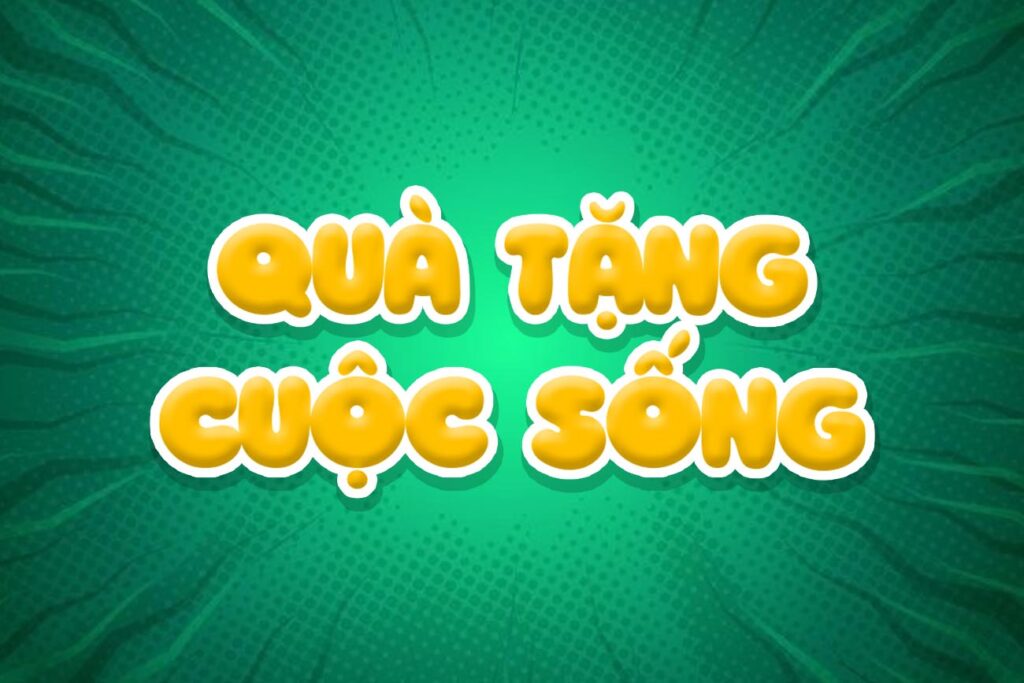
Font chữ tròn mập là nhóm phông chữ sở hữu các đường nét đầy đặn và góc bo mịn màng, mang lại cảm giác vui tươi, gần gũi và đầy năng lượng. Trong lĩnh vực kiến trúc và trang trí nội thất, việc sử dụng các kiểu chữ này giúp làm dịu đi sự thô cứng của các khối hình học, tạo nên sự cân bằng thị giác thú vị cho người xem.
Đặc điểm thẩm mỹ của dòng font chữ tròn mập trong thiết kế
Nét lôi cuốn đặc trưng của phông chữ tròn mập nằm ở cấu trúc chữ không có cạnh sắc, mô phỏng sự mềm mại của các khối hình học bo tròn. Thiết kế này tạo ra một diện mạo thân thiện, giúp thông điệp truyền tải trở nên dễ tiếp nhận và mang tính nhân bản cao hơn. Việc sử dụng font chữ bo tròn góc Việt hóa chuẩn Unicode giúp loại bỏ hoàn toàn tình trạng lỗi dấu thanh, đảm bảo các ký tự đặc biệt như “đ, ă, ơ” luôn cân đối với khung chữ chính, duy trì nhịp điệu thẩm mỹ ổn định cho văn bản.
Sự ổn định của bộ phông này còn thể hiện ở khả năng thu hút thị giác mạnh mẽ. Với trọng lượng nét dày, các kiểu chữ tròn mập chiếm lĩnh không gian hiển thị một cách có ý đồ, giúp các tiêu đề trở nên nổi bật mà không cần quá nhiều hiệu ứng đồ họa phức tạp. Đây là giải pháp phù hợp để định hình phong cách cho các không gian nghỉ dưỡng, nhà lắp ghép cho trẻ em hoặc những thương hiệu muốn khẳng định sự trẻ trung và tư duy đổi mới trong thiết kế.
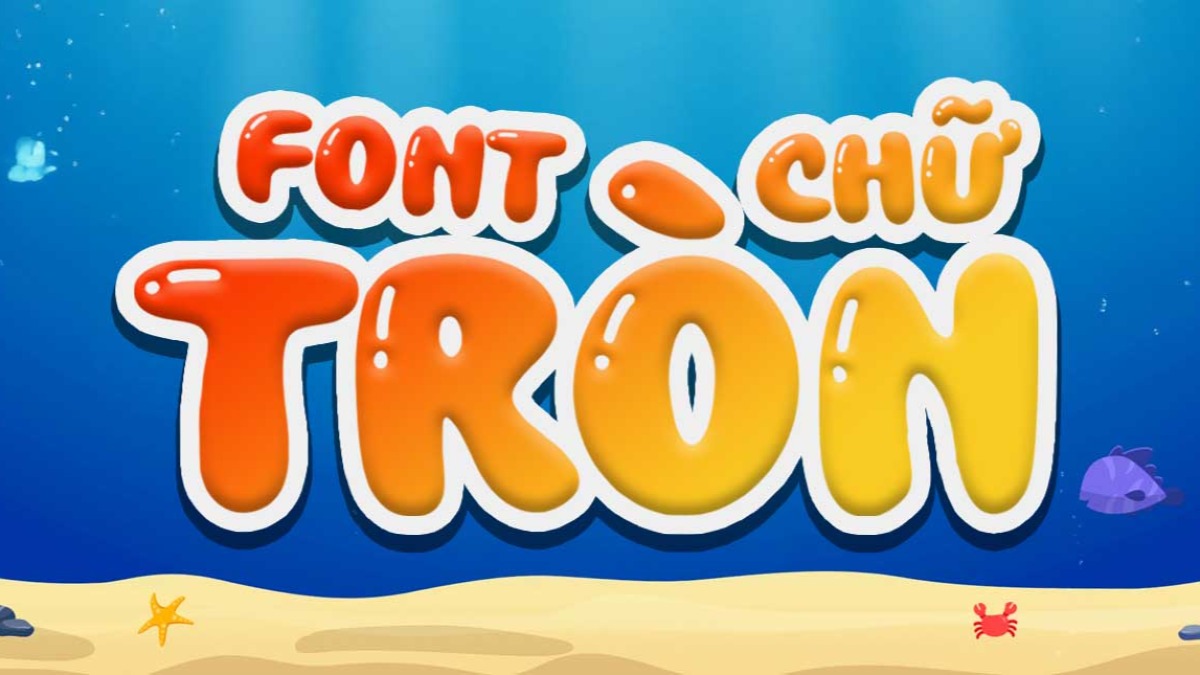
| Phân loại phong cách | Rounded Sans-serif / Display / Playful |
| Nhóm phông tiêu biểu | Baloo, Quicksand, VAG Rounded, Comfortaa |
| Mục đích phù hợp | Bảng hiệu homestay, logo, decor phòng trẻ em |
Tư vấn lựa chọn: Để bản thiết kế đạt được hiệu quả thị giác hài hòa, bạn nên phối hợp font bo tròn Việt hóa nét dày cho các tiêu đề chính và sử dụng phông tròn nét mảnh (như Quicksand Light) cho phần nội dung thuyết minh chi tiết. Sự đồng bộ về ngôn ngữ hình khối sẽ giúp hồ sơ dự án của bạn trông chuyên nghiệp và có gu thẩm mỹ riêng.
03 Ứng dụng font chữ bo tròn vào thực tế kiến trúc
Nhờ vẻ ngoài giàu tính gợi hình và sự gần gũi, bộ phông chữ này mang lại giá trị thực tế lớn trong khâu trang trí và quảng bá các công trình hiện đại:
- Hệ thống biển hiệu cho khu vui chơi & Homestay: Những nét chữ của font chữ bo tròn Việt hóa rất ăn ý khi gia công cắt nổi laser trên chất liệu nhựa màu hoặc mica. Kiểu chữ này giúp không gian toát lên vẻ thư thái, thu hút khách hàng yêu thích sự đổi mới và không gian xanh.
- Trang trí không gian nội thất mầm non: Bạn có thể dùng font tròn mập để in decal dán tường hoặc làm bảng tên góc học tập trong các căn hộ, nhà lắp ghép dành cho gia đình. Nét chữ đầy đặn tạo cảm giác an toàn và kích thích sự sáng tạo của trẻ nhỏ.
- Thiết kế Poster và Profile dự án nghỉ dưỡng: Sử dụng các biến thể đậm giúp các thông điệp về tiện ích, không gian sống trở nên dễ đọc và bắt mắt, tạo thiện cảm ngay từ cái nhìn đầu tiên đối với chủ đầu tư.
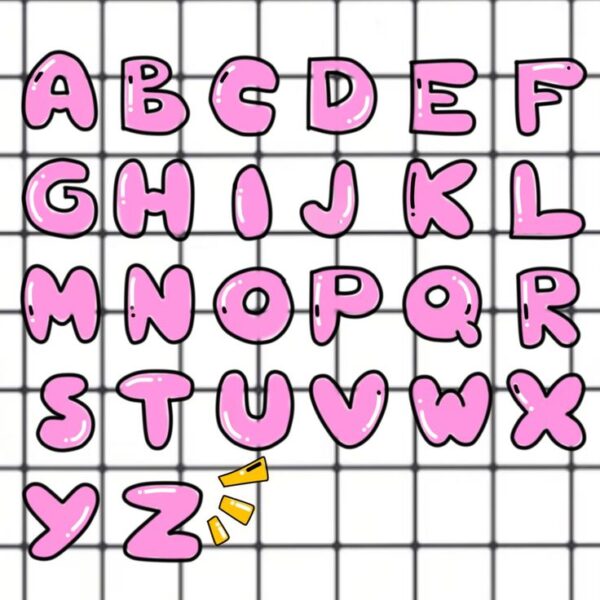
03 Lưu ý kỹ thuật để bố cục font chữ tròn mập chuyên nghiệp
Để khai thác hiệu quả vẻ đẹp của dòng font đặc thù này mà không làm rối mắt người xem, người thiết kế nên lưu tâm một số kinh nghiệm sau:
- Kiểm soát khoảng cách chữ: Do cấu trúc chữ tròn mập thường rộng ngang, các ký tự có xu hướng trông rất sát nhau ở kích thước nhỏ. Bạn nên nới rộng khoảng cách giữa các chữ cái một chút để văn bản thông thoáng và dễ nhận diện hơn.
- Hạn chế viết hoa toàn bộ ký tự: Đặc trưng của font bo tròn là sự mềm mại của các chữ cái viết thường. Việc viết hoa toàn bộ cụm từ dài có thể làm văn bản trông nặng nề và làm mất đi tính linh hoạt của bộ chữ.
- Lựa chọn màu sắc phù hợp: Font chữ tròn mập phát huy hiệu quả thị giác tốt khi phối cùng các tông màu pastel hoặc màu sắc rực rỡ, giúp tôn vinh tinh thần năng động và hiện đại của bản thiết kế.